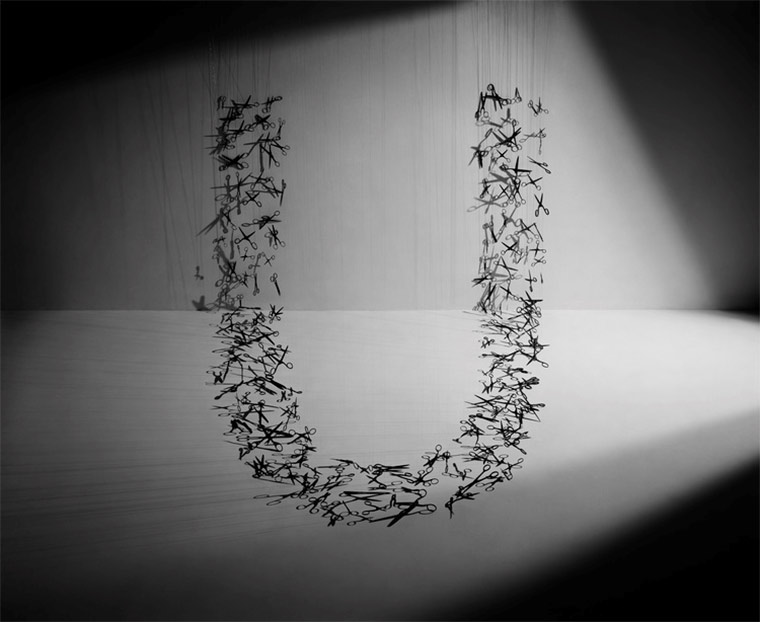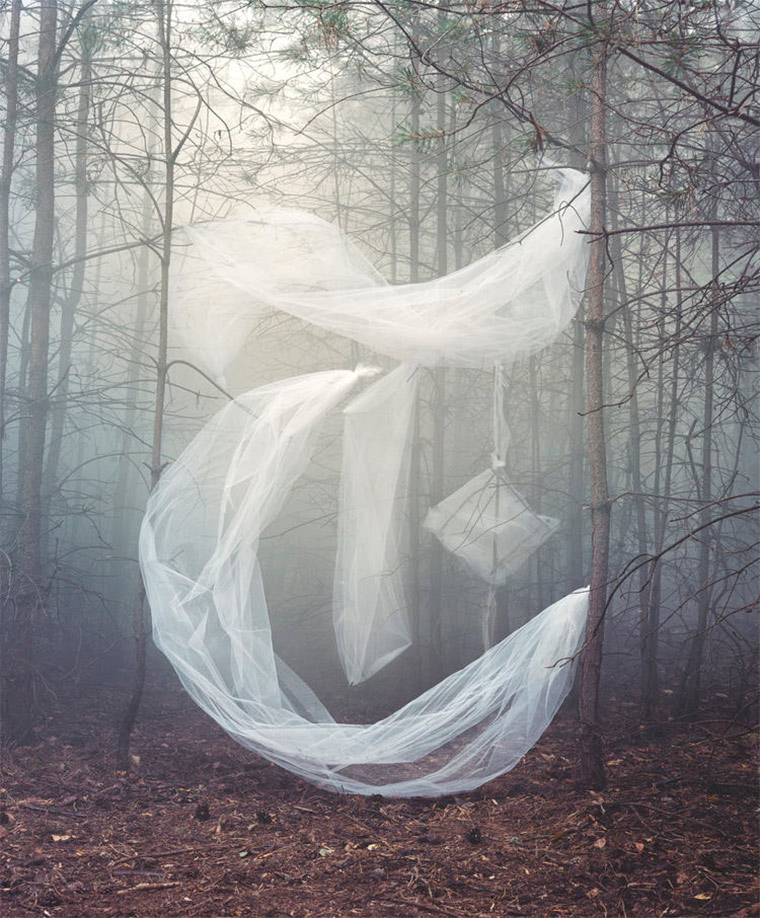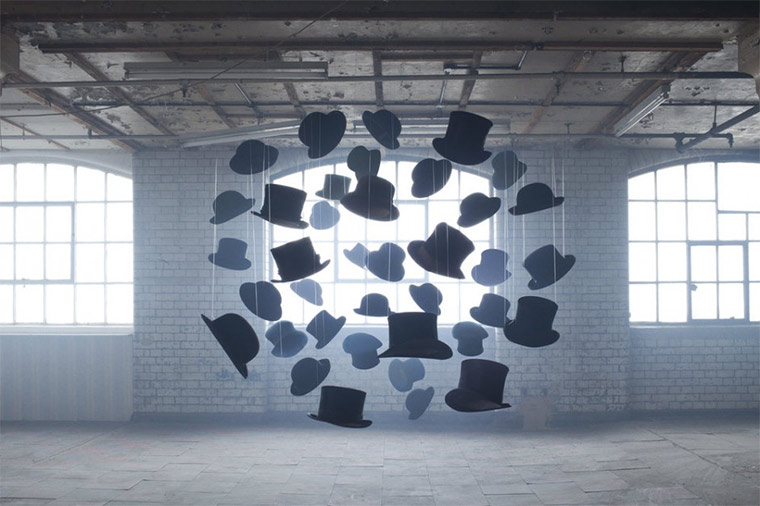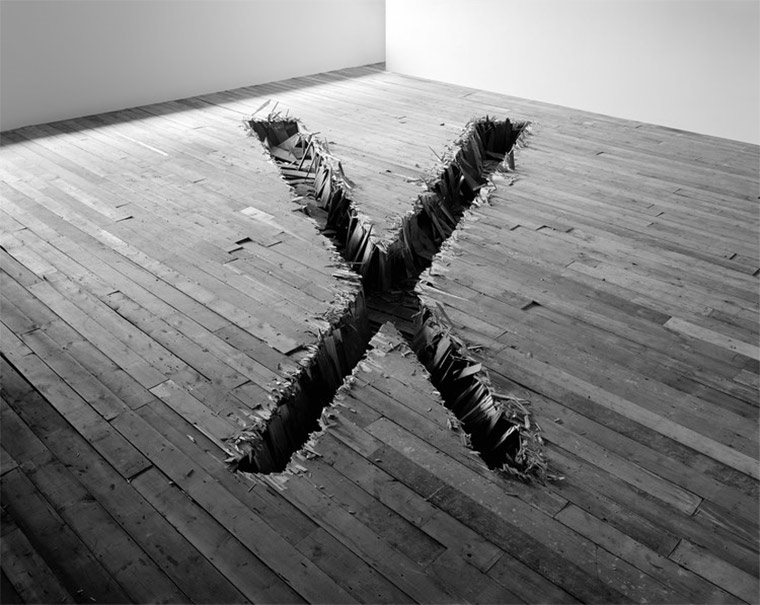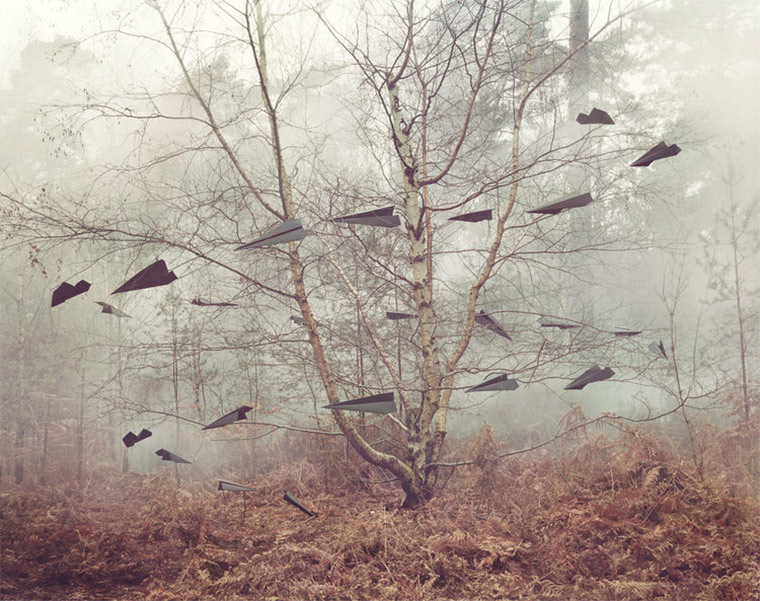
ausgeklügelte Kunst von Nicola Yeoman
Typografie-Illusionen
Die Set-Designerin Nicola Yeoman nimmt gerne alltägliche Gegenstände, drapiert sie gekonnt im Raum oder hängt sie in der Luft auf und lässt so gigantische Buchstaben entstehen. Oder alternativ auch einfach nur schön anzuschauende Skulpturgebilde. Oder beides. Jedenfalls sehr außergewöhnliche Motive, wobei mir die Typografie-Arbeiten mit Abstand am besten gefallen, hierbei besonders das „D“ und das „X“.